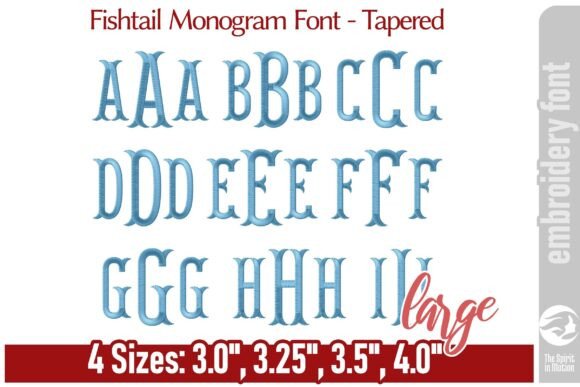
Fishtail Monogram Font - Tapered / L
Якщо ви шукаєте високоякісні ресурси, такі як Fishtail Monogram Font - Tapered / L, цей преміум-пакет є фантастичним вибором для ваших творчих проектів.
Створений з високою точністю, Fishtail Monogram Font - Tapered / L забезпечує чисті вектори, плавну типографіку та комерційну ліцензію для вашого спокою.
Незалежно від того, чи створюєте ви продукти POD (друк на вимогу), весільні запрошення або графіку для соціальних мереж, Fishtail Monogram Font - Tapered / L стане ідеальним вибором.